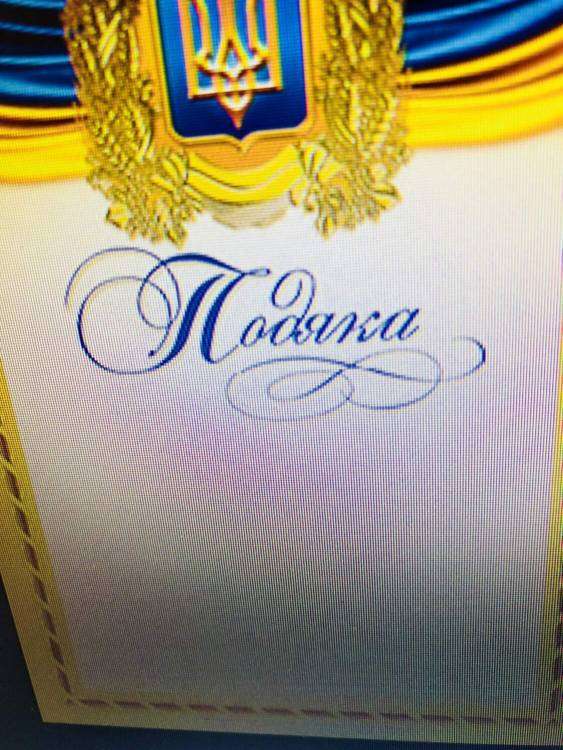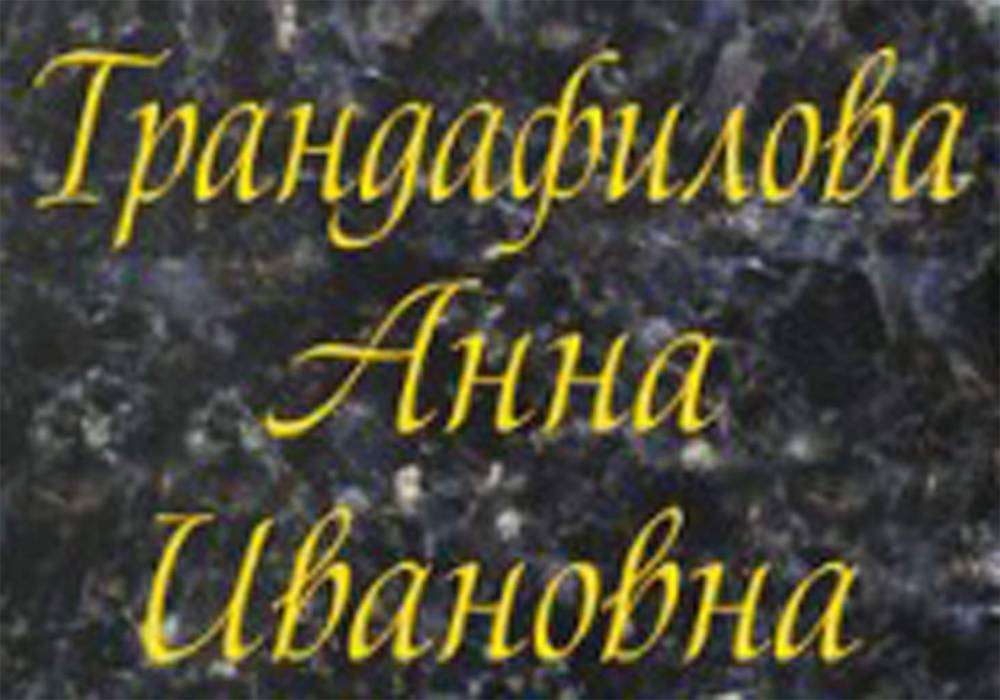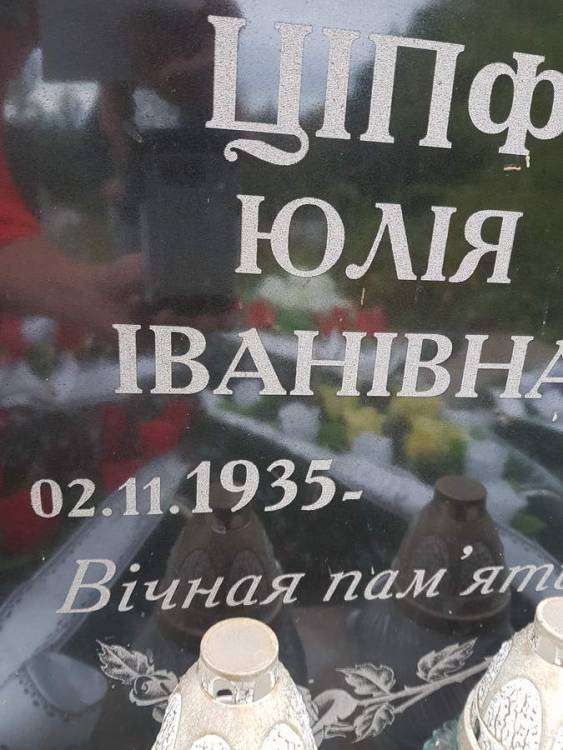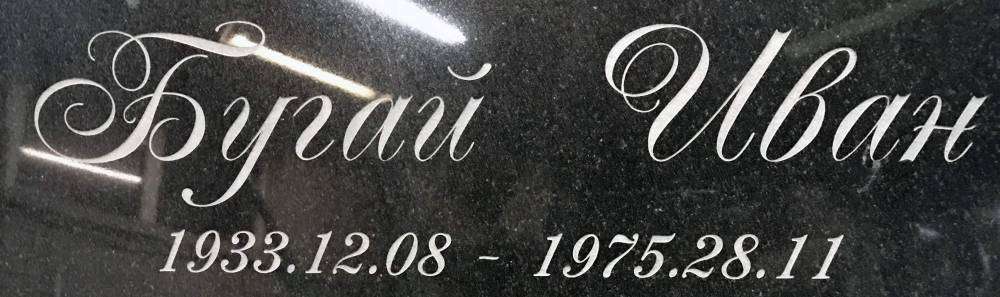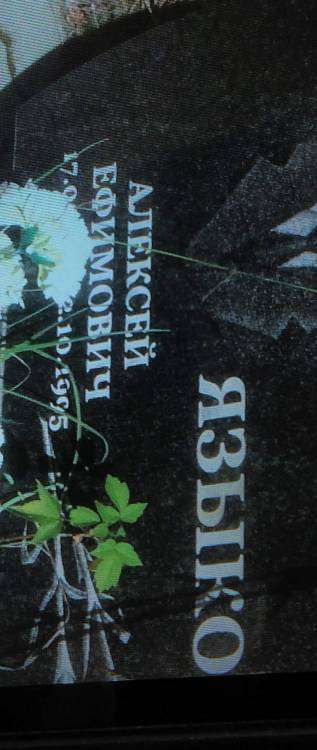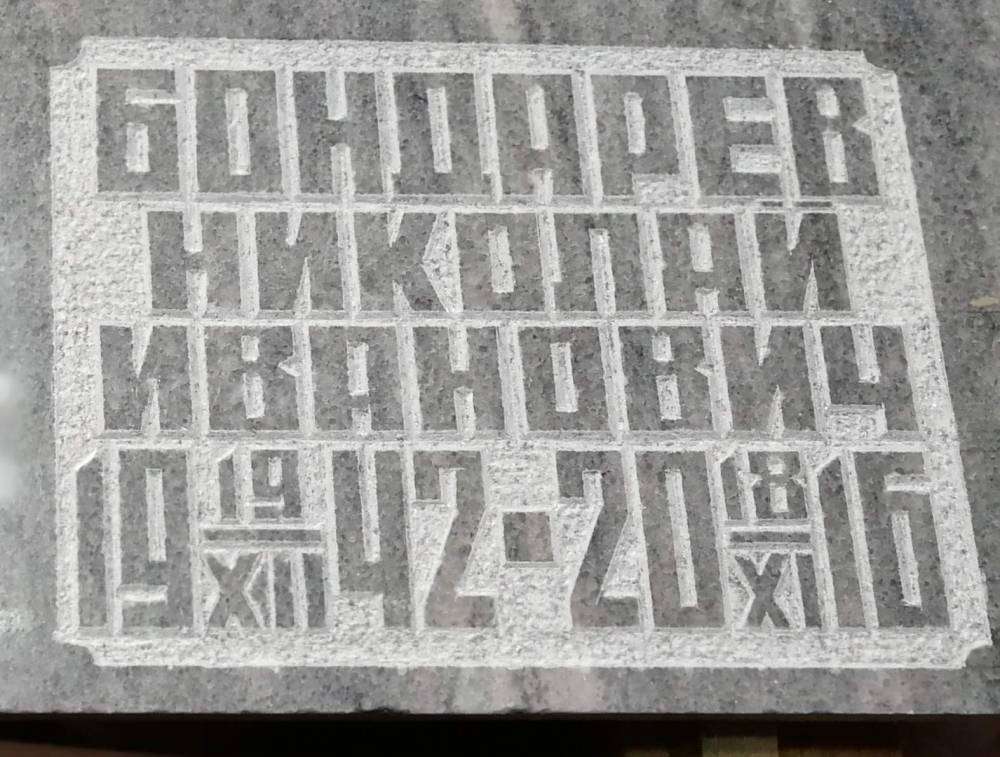
Помогите найти шрифт!
Ребята,  специалисты по шрифтам! Помогите определить название шрифта пожалуйста. Пересмотрела кучу материала в инете, так и не подобрала.
Arial - regular )))
это я про шрифт, которым стартовый топик написан - другого не вижу
Подскажите, пожалуйста, шрифт - характерная буква "З"
и засечки изогнутые
Помогите пожалуйста найти этот стандартный шрифт для ручной гравировки по мрамору.
Самый близкий пока нашел этот
@4elovek73 Расчитайте сами.  На букву 2,5 см. Из расчета 1 см ножка буквы, промежуток между ножками 0,5 см. Между буквами тоже 0,5 см.  Итого на фамилию Бондарев, нужно 23 см, Опять же если нужно руками гравировать. А так....a_MachinaOrto Bold думаю подойдет.
Ужас какой то...
Рубить такое - себя не уважать.
Подскажите пожалуйста что за шрифт на фото
Шрифт Majestic
Подскажите, пожалуйста, название шрифта. Хотят именно такой
a_AvanteTck
a_AvanteBs
Вообще подходит любой из этого семейства.
Добрый день. Подскажите пожалуйста шрифт даты
Academia
не уверен за написание названия, но как-то так.